Font chữ Thái là nhóm phông chữ đặc thù mô phỏng cấu trúc đường nét uyển chuyển của hệ văn tự xứ chùa vàng, nổi bật với các vòng khuyên đầu chữ và những đường uốn cong mềm mại mang đậm bản sắc văn hóa Đông Nam Á. Với vẻ ngoài độc đáo, giàu tính biểu tượng và dễ nhận diện, font chữ Thái Lan là chất liệu trực quan tuyệt vời để các kiến trúc sư, nhà thiết kế kiến tạo phong cách cho các bản vẽ phối cảnh quán ăn ẩm thực đường phố, tiệm trà Thái container hay khu spa trị liệu phong cách mộc mạc.
Đường nét uốn lượn có móc đầu đặc trưng của font chữ Thái Lan
Điểm cuốn hút của font chữ kiểu Thái Lan nằm ở sự kết hợp giữa nét chữ Latinh hiện đại và các chi tiết cách điệu mô phỏng chữ cái tiếng Thái như nét móc tròn khép kín, thân chữ hơi nghiêng và các đường lượn mềm mại. Thiết kế này tạo nên sự liên tưởng trực giác mạnh mẽ đến văn hóa ẩm thực và du lịch nhiệt đới ngay từ cái nhìn đầu tiên.
Bên cạnh phong cách truyền thống, các dòng font chữ Thái hiện đại (không có vòng khuyên đầu chữ – Loopless Thai Style) đang ngày càng được ưa chuộng nhờ sự giao thoa giữa tính dân tộc và phong cách tối giản quốc tế. Khi xuất hiện trên các vật liệu xây dựng hiện đại như tấm panel tôn phẳng sơn màu vàng rực, vách nan tre nứa hay hộp đèn mica hút nổi, kiểu chữ này tạo nên sự tương thích thẩm mỹ cao.
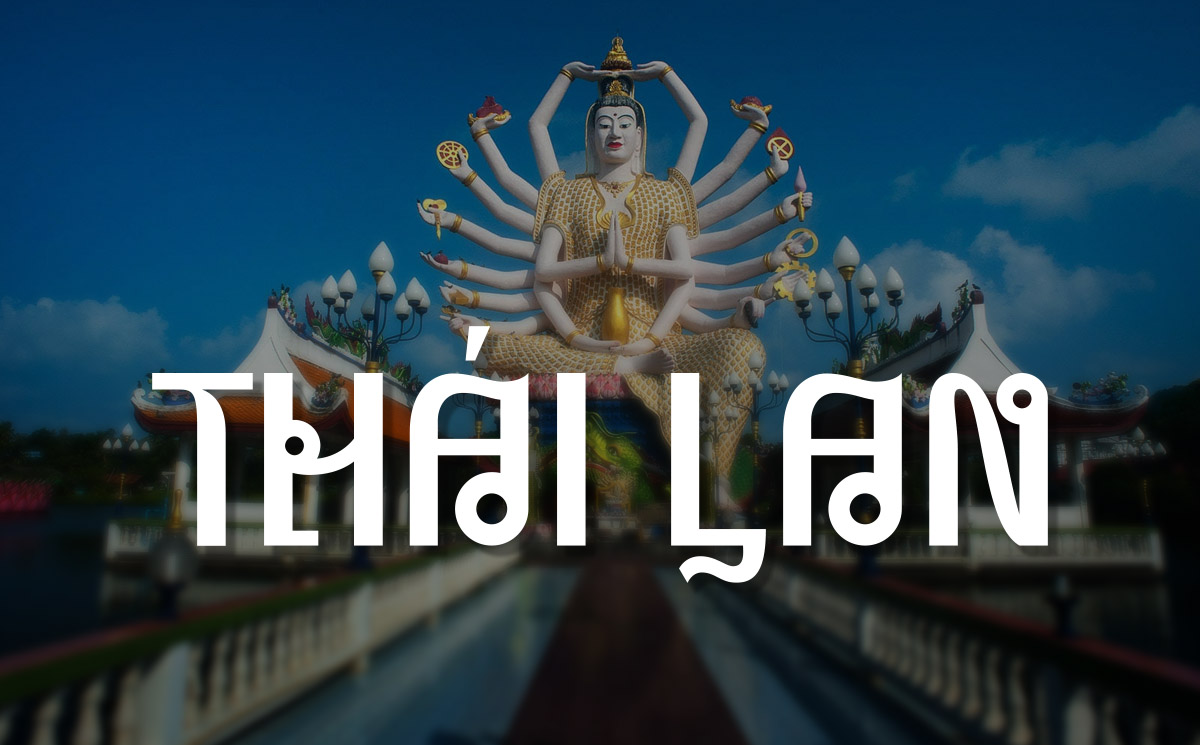
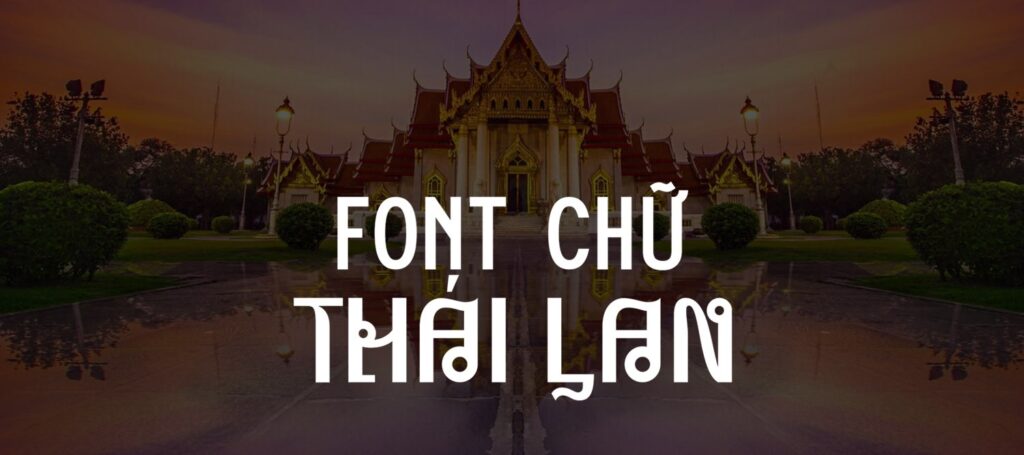
Tư vấn từ chuyên viên: Font chữ Thái Lan đẹp sở hữu nét tạo hình giàu tính bản địa. Để bản thiết kế đạt hiệu quả thẩm mỹ tốt, bạn nên sử dụng phông chữ này cho các tiêu đề chính, tên quán hoặc món ăn đặc trưng. Phần nội dung mô tả kỹ thuật chi tiết nên đi kèm một phông chữ không chân thanh mảnh hơn để người xem tiếp nhận thông tin dễ dàng.
03 Ứng dụng phông chữ kiểu Thái Lan vào công trình thực tế
Nhờ vẻ ngoài đặc sắc và khả năng gợi nhớ văn hóa mạnh mẽ, bộ phông chữ này mang lại giá trị thực tế lớn trong khâu hoàn thiện các mô hình kinh doanh dịch vụ:
- Hệ thống biển hiệu cho Quán Ăn và Tiệm Trà Thái Container: Những ký tự có móc tròn của phông chữ kiểu Thái rất ăn ý khi gia công chữ nổi bằng mica màu cam cháy hoặc vàng tươi gắn đèn LED trên nền tôn sóng, mang lại diện mạo rực rỡ và đậm chất ẩm thực xứ Chùa Vàng.
- Bảng chỉ dẫn và Biển tên phòng Khu Spa Trị liệu: Sử dụng font chữ Thái Lan hiện đại kết hợp cùng chất liệu gỗ tự nhiên sơn bóng mờ sẽ giúp các căn homestay lắp ghép toát lên vẻ thư thái, mang lại cảm giác an yên cho khách hàng đến thư giãn.
- Thiết kế bìa hồ sơ giải pháp ki-ốt thương mại: Áp dụng font chữ tiếng Thái Lan vào bản vẽ thuyết minh chuỗi quầy bán hàng lưu động giúp chủ đầu tư dễ dàng hình dung sự tương thích giữa kiến trúc và phong cách món ăn kinh doanh.
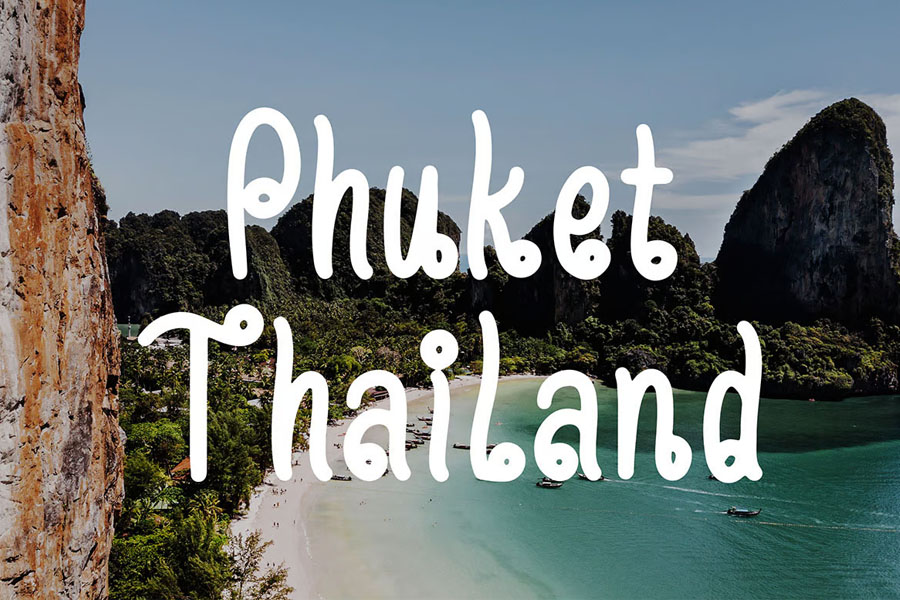
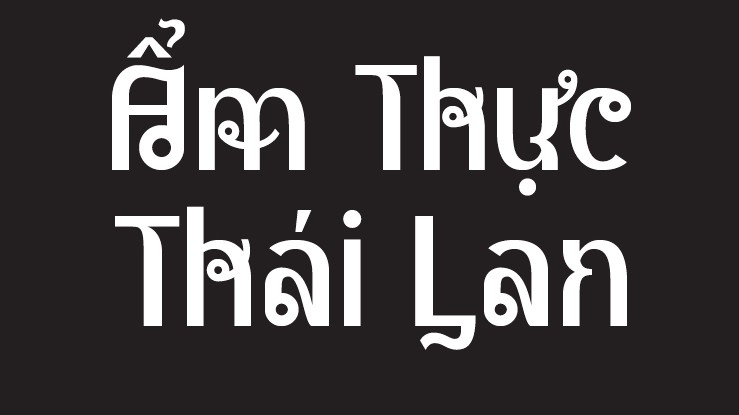
03 Lưu ý bố cục font chữ Thái hiện đại luôn rõ nét và bắt mắt
Để khai thác hiệu quả vẻ đẹp của dòng font đặc thù này mà không gây cảm giác khó đọc cho thực khách, người thiết kế nên lưu tâm một số kinh nghiệm sau:
- Kiểm soát khoảng cách ký tự: Do chữ có nhiều chi tiết vòng tròn và móc cong, bạn nên nới rộng nhẹ khoảng cách giữa các chữ cái để câu chữ thông thoáng, tránh hiện tượng dính nét khi quan sát từ cự ly xa trên các biển hiệu ngoài trời.
- Tránh sử dụng cho đoạn văn bản dài: Cấu trúc giả nét chữ Thái có thể gây hiểu nhầm hoặc làm chậm tốc độ đọc nếu trình bày ở kích thước nhỏ. Hãy giới hạn trong các cụm từ ngắn từ 2 đến 4 từ như tên thương hiệu hoặc slogan ngắn gọn.
- Lựa chọn gam màu nhiệt đới rực rỡ: Phông chữ phát huy hiệu quả thị giác cao khi phối cùng các tông màu mang sắc thái ẩm thực Thái như cam đất, vàng nghệ, xanh lá chuối hoặc tím hoa lan trên nền gỗ trầm, làm nổi bật đường nét văn hóa của bộ chữ.